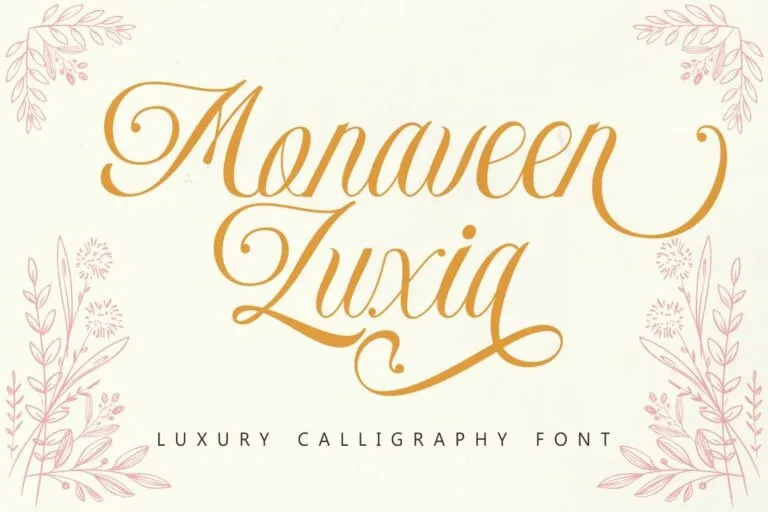
Monaveen Luxia Font – Fonte Grátis
Monaveen Luxia Font
A Monaveen Luxia é uma fonte de script elegante e versátil criada pelo estúdio PutraCetol Studio. Esteu design inclui diversos estilos alternativos, ligaturas, espigas e caracteres para várias línguas, proporcionando infinitas possibilidades de criação. A Monaveen Luxia foi concebida para trabalhar em harmonia perfeita, tornando-a ideala para uma vasta gama de projetos, incluindo materiais de casamento, capas de livros, cartões de felicitações, logotipos, marcação, cards de visita e certificados. Ela também se destaca como a escolha ideal para qualquer trabalho gráfico que demande um estilo elegante ou luxuoso. Este é o tipo de fonte que fará seu projeto brilhar ainda mais.